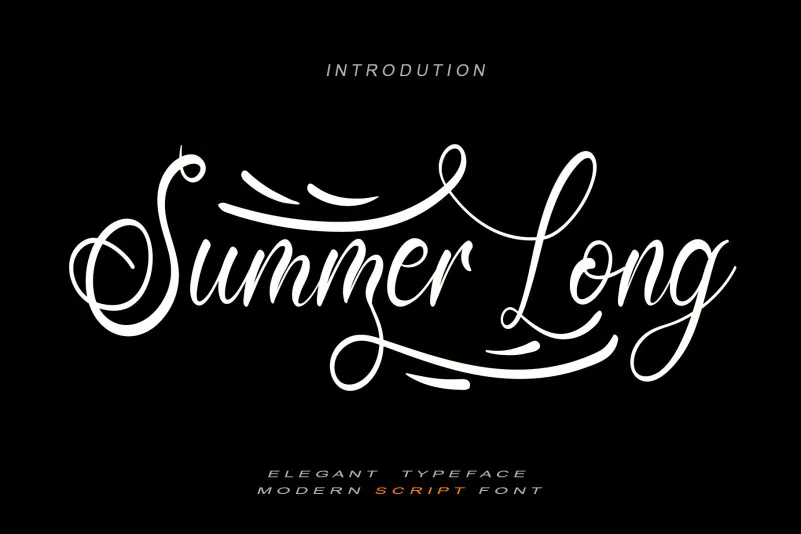
Summer Long Font – Download Grátis
Esta é uma fonte handwritten delicada e suave com letras distintas e equilibradas perfeitamente. Seus traços elegantes tornam a fonte não apenas uma opção versátil, mas também um verdadeiro trabalho de arte. Ela traz consigo um toque sofisticado que é ideal para criar designs extraordinários. Para quem busca um estilo único e harmonioso nas criações digitais, esta é uma escolha perfeita. Suas linhas curvadas e sua textura natural se adaptam perfeitamente a qualquer projeto gráfico que você possa ter. Seja para design de publicidade, ilustrações ou até mesmo para personalizar suas próprias mensagens em redes sociais — essa fonte será uma escolha inteligente.